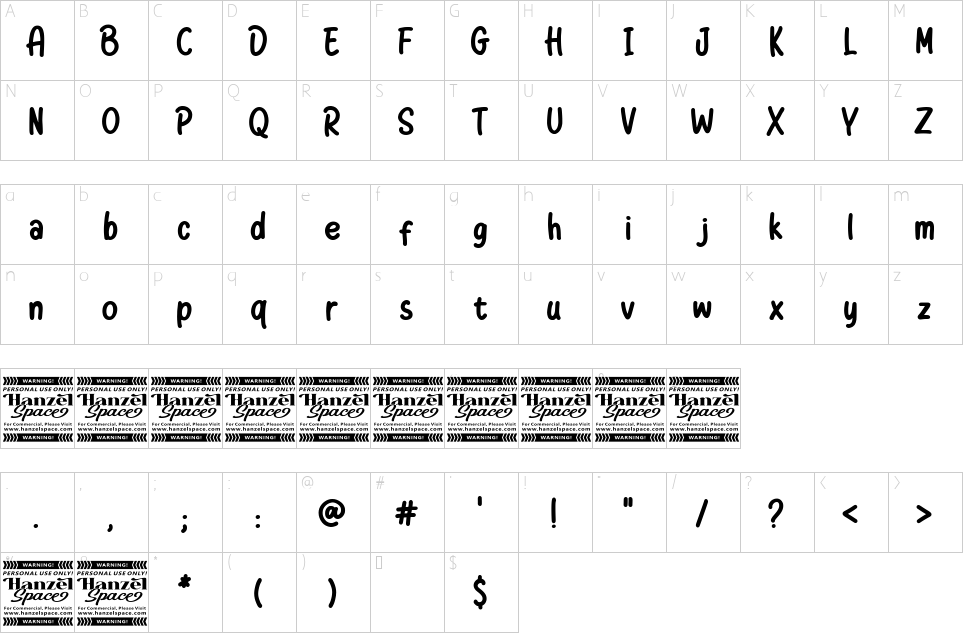
A fonte Just Squash, um belo aditivo para qualquer projeto gráfico, foi criada por Hanzel Space. Ela é uma opção gratuita que oferece uma variedade de tamanhos e tipografias, tornando-a uma excelente escolha para designers gráficos que buscam um estilo único e alegre em seus trabalhos. O Just Squash font foi baixado 8.161 vezes por designers que apreciam sua simplicidade e criatividade. Ideal para criar designs que exalam leveza e bom humor, a Just Squash font é uma excelente opção para aqueles que estão procurando por uma fonte de qualidade para projetos de criação gráfica, seja para editoriais, sites ou materiais de marketing.